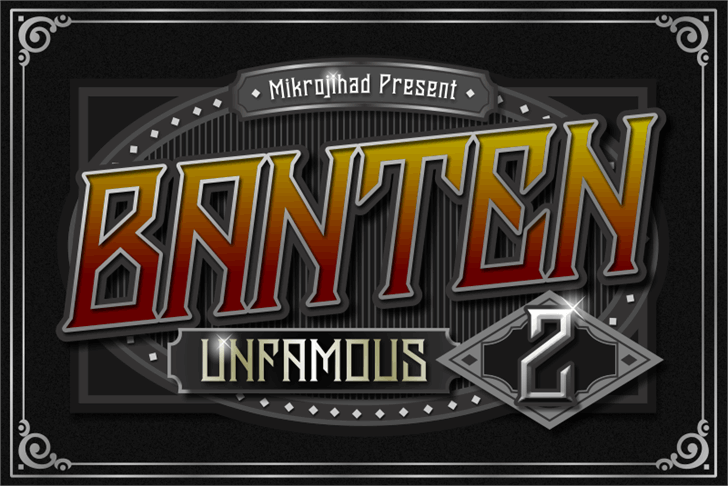
A Banten Unfamous 2 é uma elegante e moderna fonte display que traz um toque único para qualquer projeto visual. Desenvolvida por Hamilton em 2014, essa fonte oferece linhas levemente curvas e cores vibrantes, combinando perfeitamente com o estilo de desenho de Hamilton. Seu design é notável pela simplicidade que exibe profundas nuances estilísticas, tornando-a uma escolha ótima para designers em busca de um pouco de diversão no mundo do tipo digital. Conheça essa fonte e descubra por si mesmo o poder da Banten Unfamous 2 para transformar seus projetos digitais.